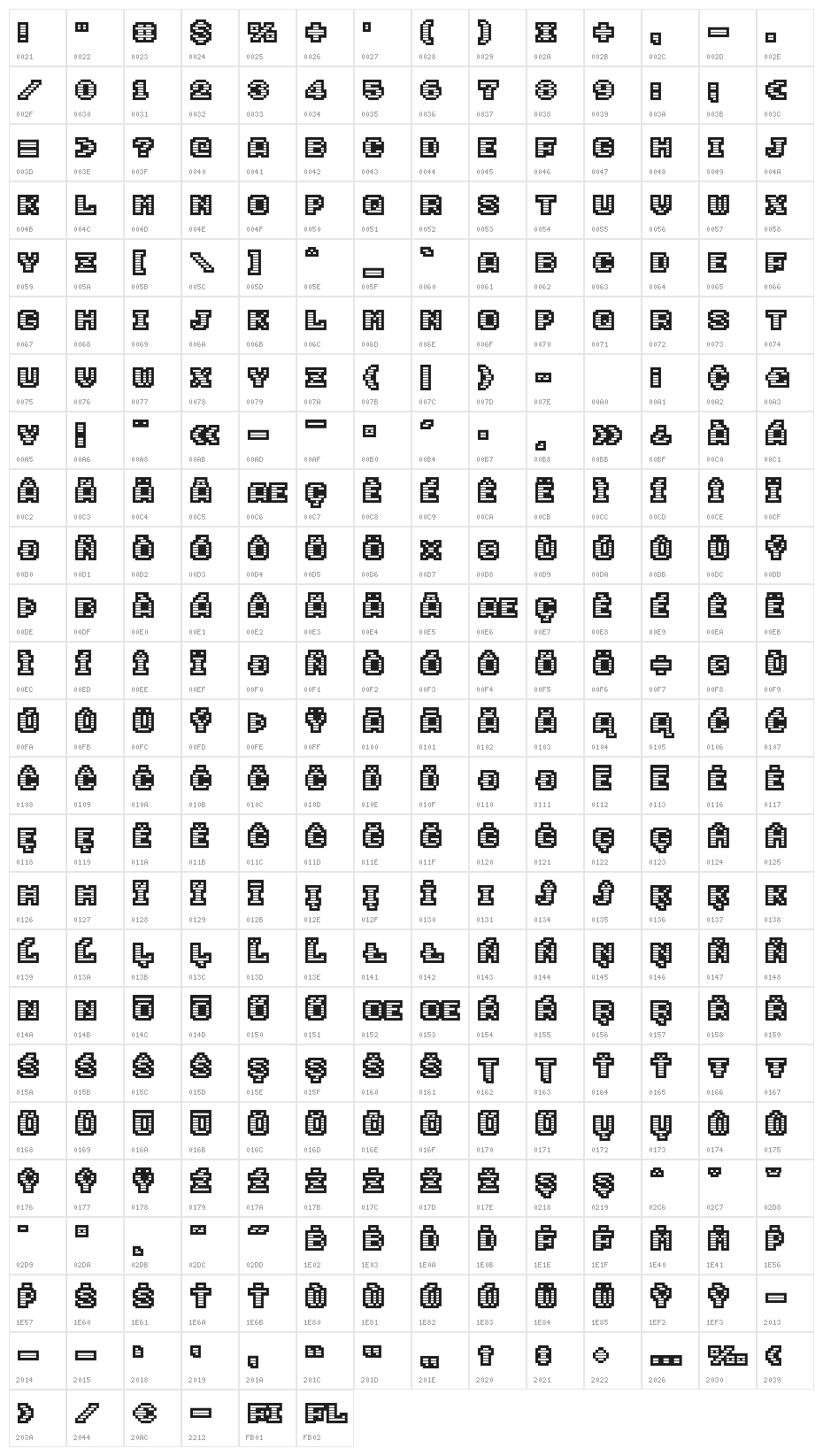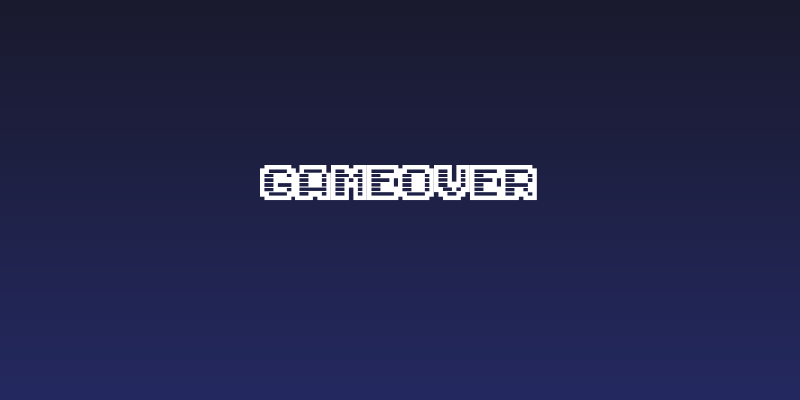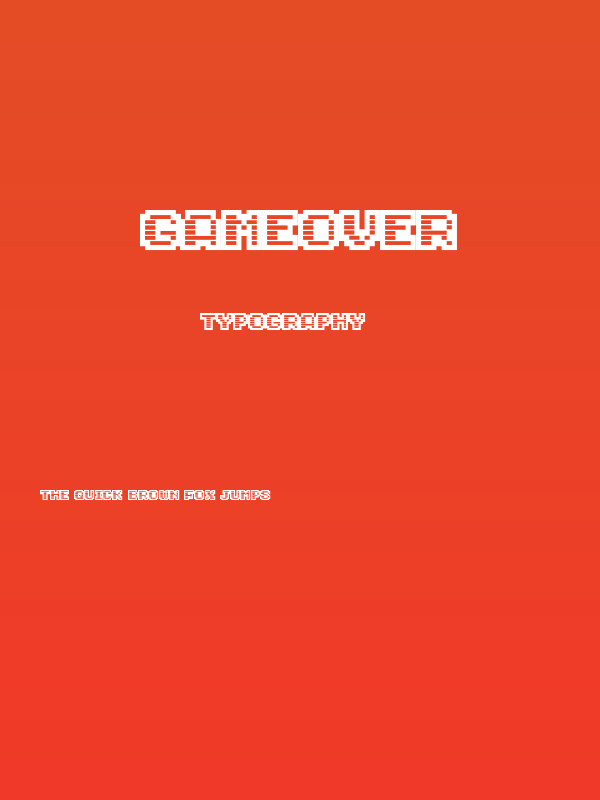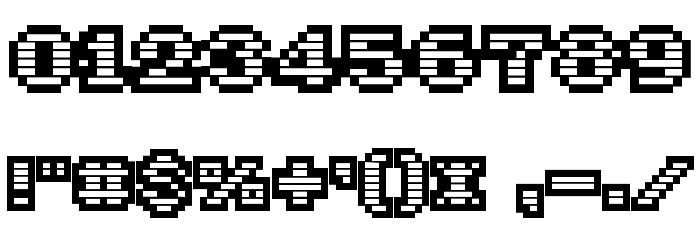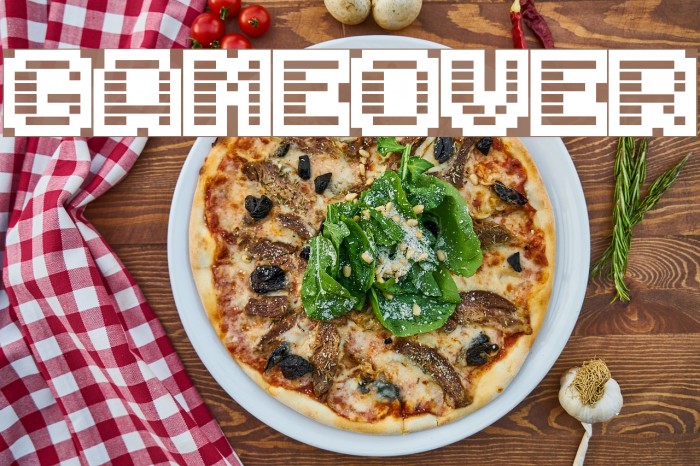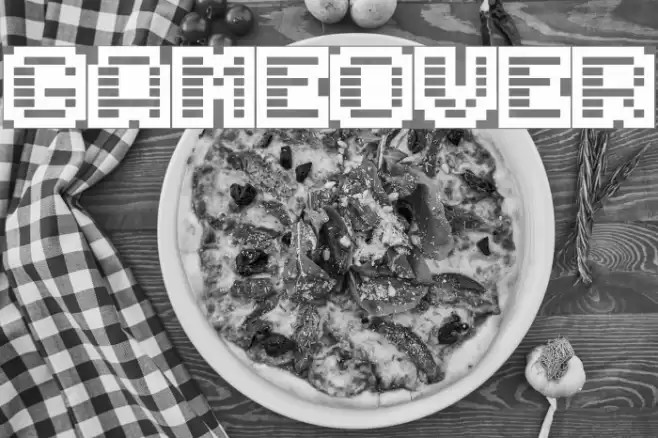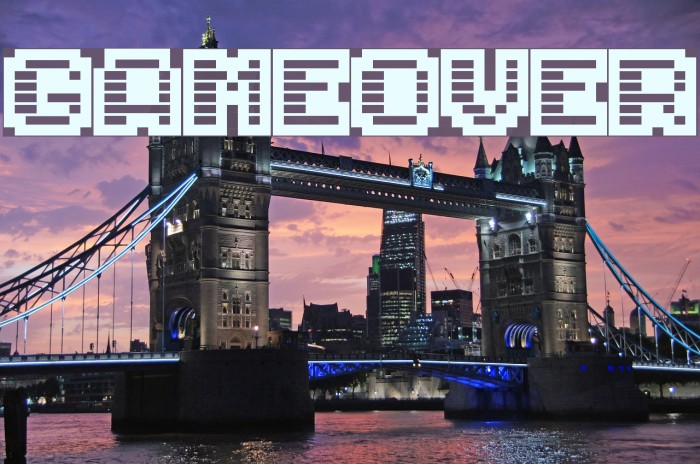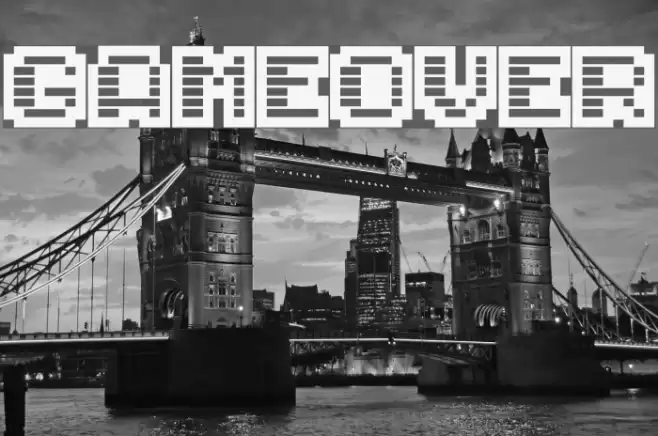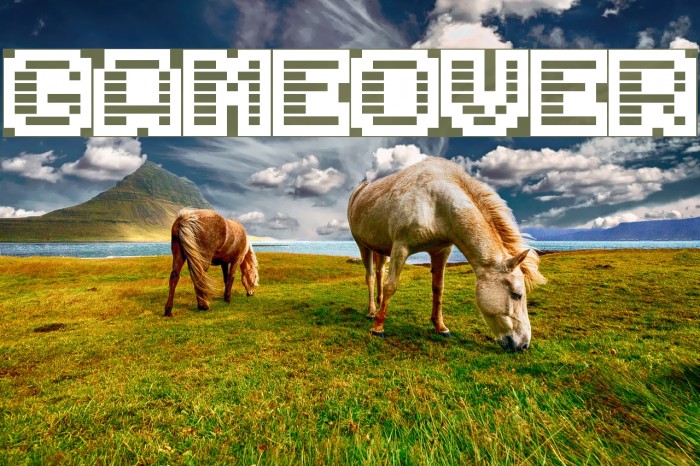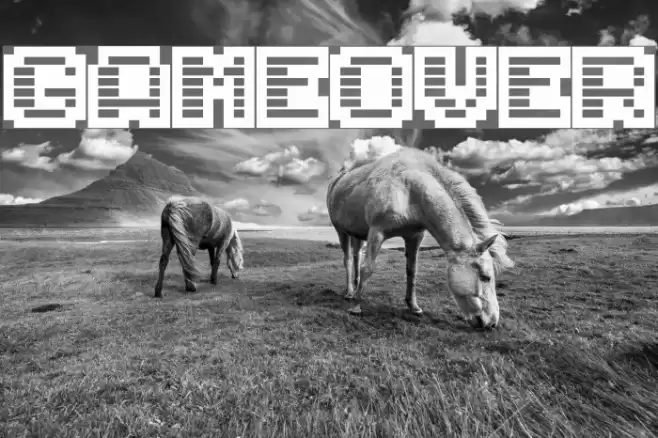
Gameover Font
| Estilo general | Vintage |
| Proyectos propuestos | Ideal for video game designs, retro-themed posters, digital art projects, and any creative work that seeks to evoke nostalgia for classic arcade games. |